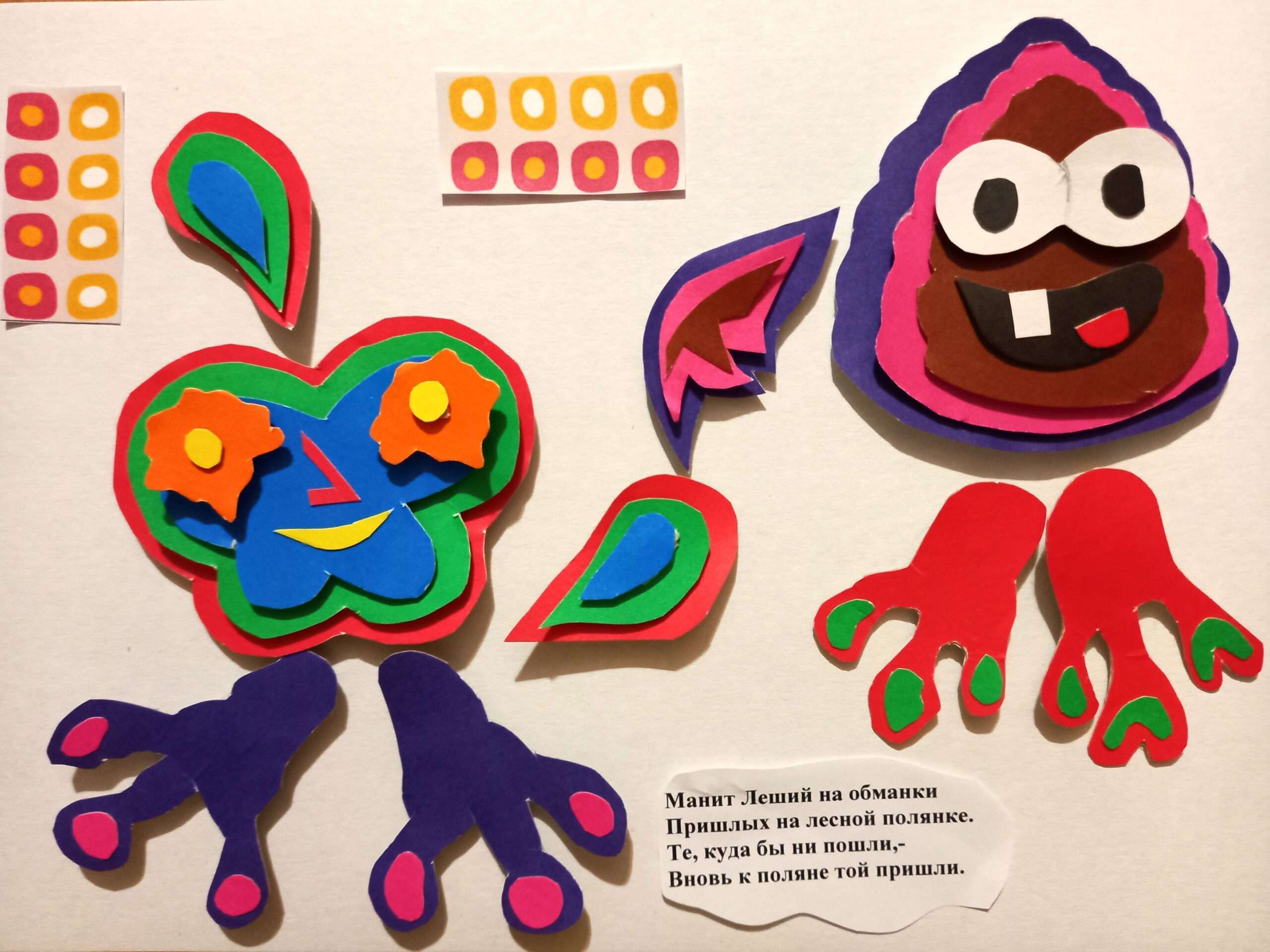
Буква И. Шрифт Леший. Девиз работы: радуйтесь сами и радуйте других!
Буква изображена в виде озорных, смешных и совсем незлых леших. Творческая аппликация, многослойное наложение деталей. В жанре фэнтези. Цветовое разнообразие делает всех вокруг разноцветными и счастливыми. К букве приложены стихи Геннадия Дергачева.